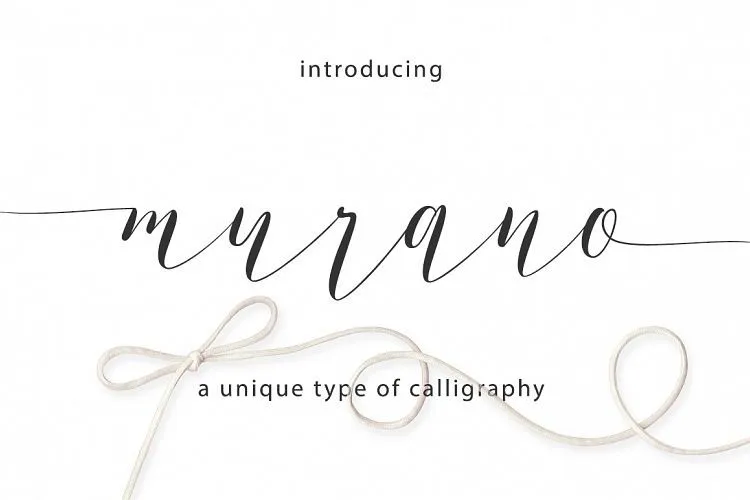
Murano Script Font é uma fonte script chamada com estilo elegante e sofisticado, inspirada na caligrafia. É perfeitamente adequada para design de moda, casamentos e identidades gráficas. Ela vem com caracteres bonitos que mudam a cada nova linha de texto e está elaboradamente detalhada para proporcionar um ar elegante e moderno. Foi projetado especificamente como uma caligrafia flat top, ou seja, sem ponteirões em sua base, garantindo-lhe um design simples mas muito sofisticado. Murano Script Font será perfeita para vários tipos de projetos, desde slogans e cabeçalhos de blogs até postais e material de convites. Ela também é ótima para letras, logotipos, roupas e ações de marketing. Com suas linhas elegantes e formas criativas, Murano Script Font traz um toque inovador às suas criações.